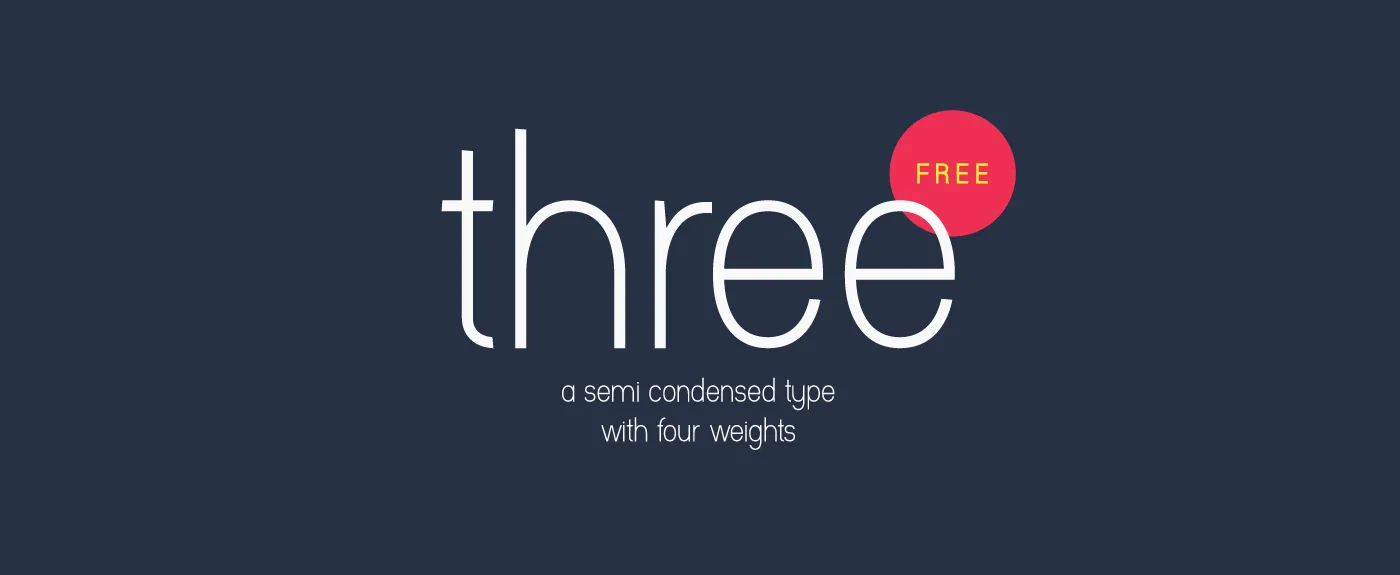
A fonte “Three Font” é uma nova escolha gratuita para designers e criadores de conteúdo digitais. Este tipo de fóntes sans serif apresenta traços semi-condicionados, combinando elegância minimalista com um design limpo e simples. É a primeira fonte no qual Hamilton utilizou apenas círculos como elemento de design, o que dá à letra uma certa versatilidade e originalidade. Seja para criar textos informativos ou artigos modernos, “Three Font” oferece uma aparência clean sem comprometer as capacidades expressivas da fonte. Inspirado na simplicidade elegante, a esperança é que você se divirta experimentando esta nova opção de fonte.